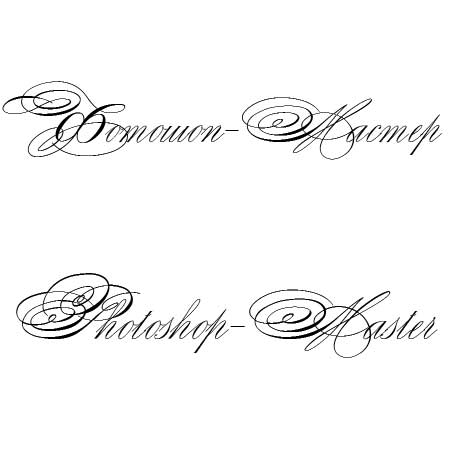
шикарный шрифт!
Романтичный шрифт)
Очень красивый шрифт
Очень красиво!
Супер)) ваще класс
Величезне дякую! Неймовірний шрифт!!!
Шрифт просто бесподобный!!!
ПРикольно! но очень много завитушей